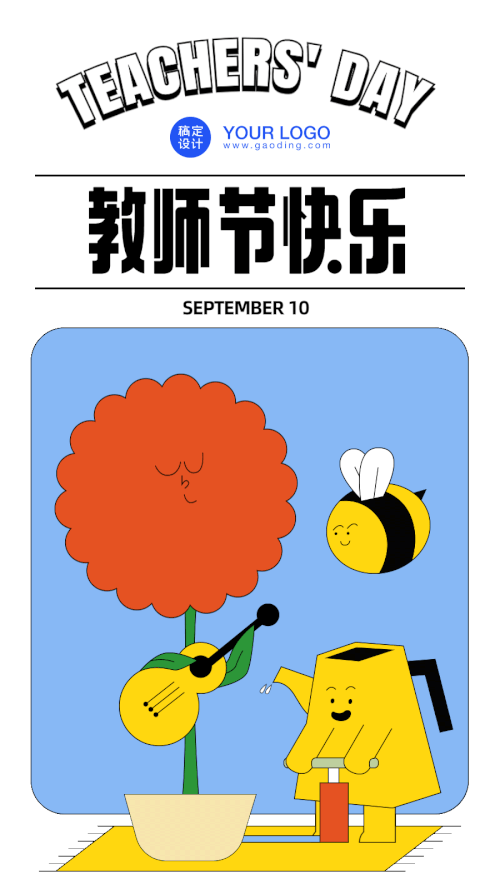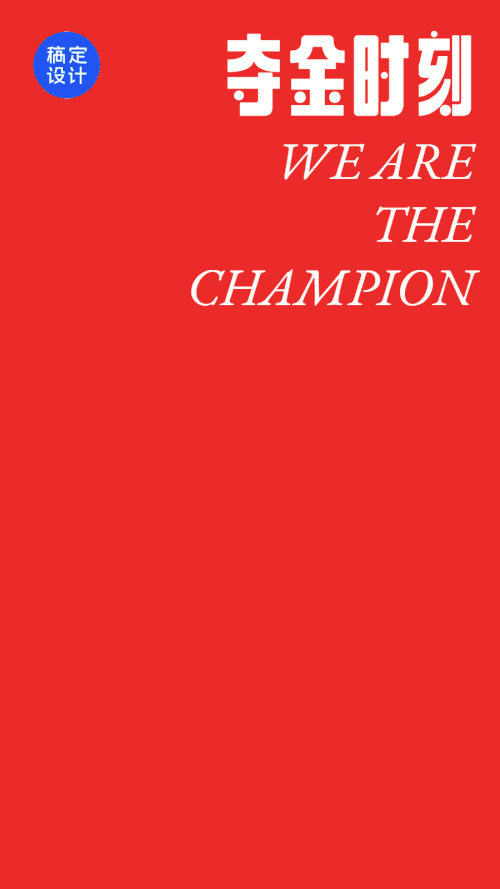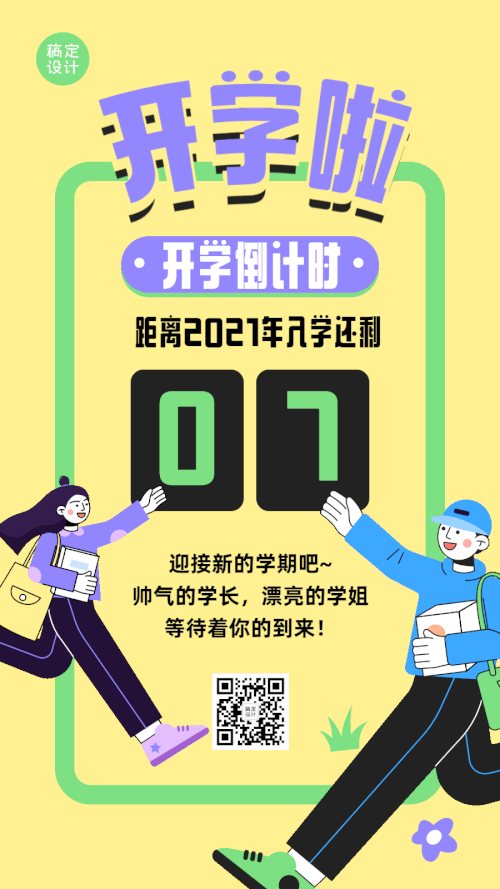
字由芳华体
字由芳华体是字由品牌推出的一款创意字体,以“有趣”为核心设计理念,兼具视觉张力与实用价值,为各类设计场景注入鲜活灵感。 字由芳华体整体字形修长,重心居中且中宫适中,纵向延伸的比例让文字在视觉上更显舒展大气,既保留了字体结构的稳定性,又通过灵动的轮廓打破沉闷,展现出独特的韵律感。 字由芳华体的笔型设计充满巧思:笔画末端融入独特的装饰元素,搭配圆润饱满的笔画形态与部分连笔设计,让每一笔都自带趣味属性。这些细节不仅打破了常规字体的刻板印象,更赋予文字活泼灵动的个性,尽显设计师的匠心巧思。 作为一款字重偏粗的字体,字由芳华体笔画粗细均匀,线条扎实有力,既能保证文字的高识别度,又能在海报、品牌宣传、社交媒体排版等场景中形成鲜明的视觉焦点。更值得关注的是,字由芳华体支持免费商用授权,字符集覆盖常规中文,无论是文创产品设计还是商业宣传物料,都能轻松适配,是创作者兼具美感与实用性的理想选择。